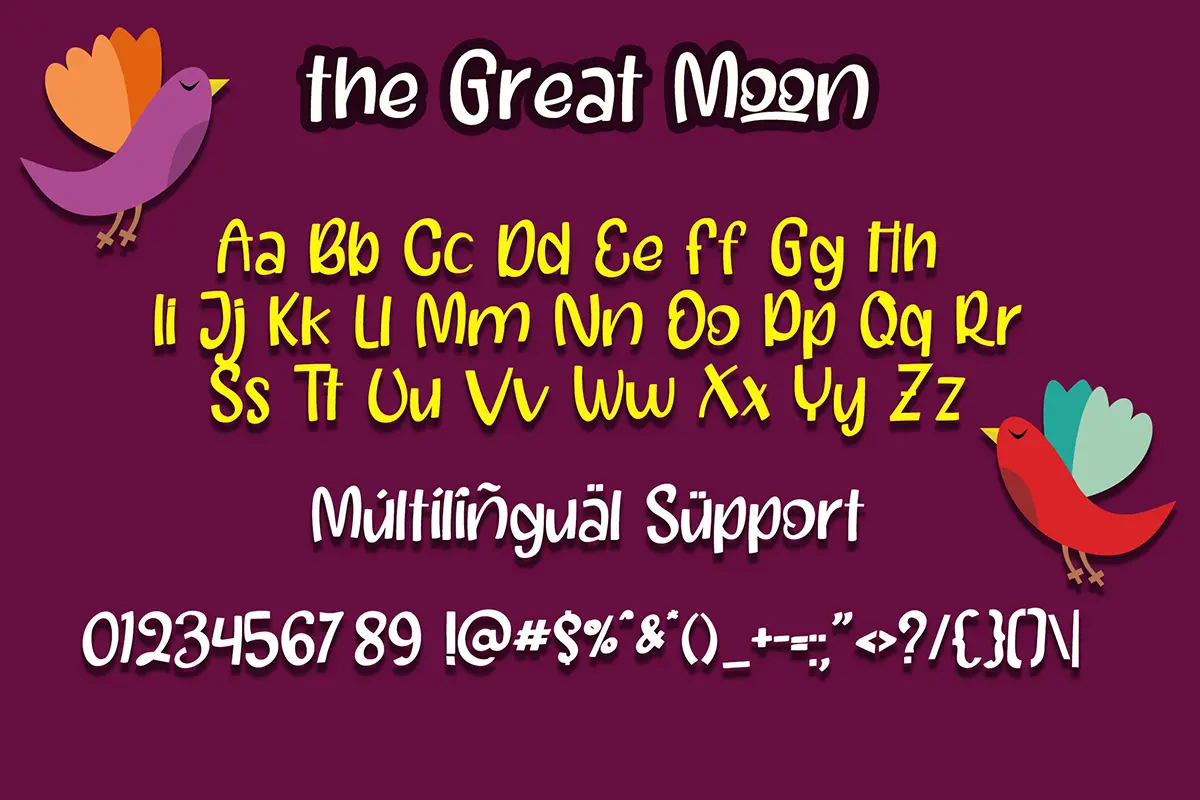
فونت دست نویس خلاق
فونت The Great Moon یک فونت دست نویس جذاب و پرانرژی است که با سبک دوستانه و غیررسمی خود، به پروژههای شما روح تازهای میبخشد. این فونت با حالوهوای خلاقانه و بازیگوش، انتخابی عالی برای طراحیهای متنوع است و به راحتی با طیف گستردهای از پروژهها هماهنگ میشود.
⭐ ویژگیهای کلیدی
- سبک دستنویس مدرن و سرگرمکننده
- مناسب برای پروژههای چاپی و دیجیتال
- طراحی ساده اما چشمگیر برای جلب توجه مخاطب
- قابل استفاده در تیترها، لوگوها و متنهای کوتاه
🎯 موارد استفاده پیشنهادی
- طراحی کارتهای تبریک و دعوتنامههای دوستانه
- پروژههای خلاقانه کودکان و صنایع دستی
- پستهای شبکههای اجتماعی با حالوهوای صمیمی
- طراحی لوگوهای غیررسمی و سرگرمکننده
- استفاده در پوسترها، برچسبها و بستهبندیهای سبکدار